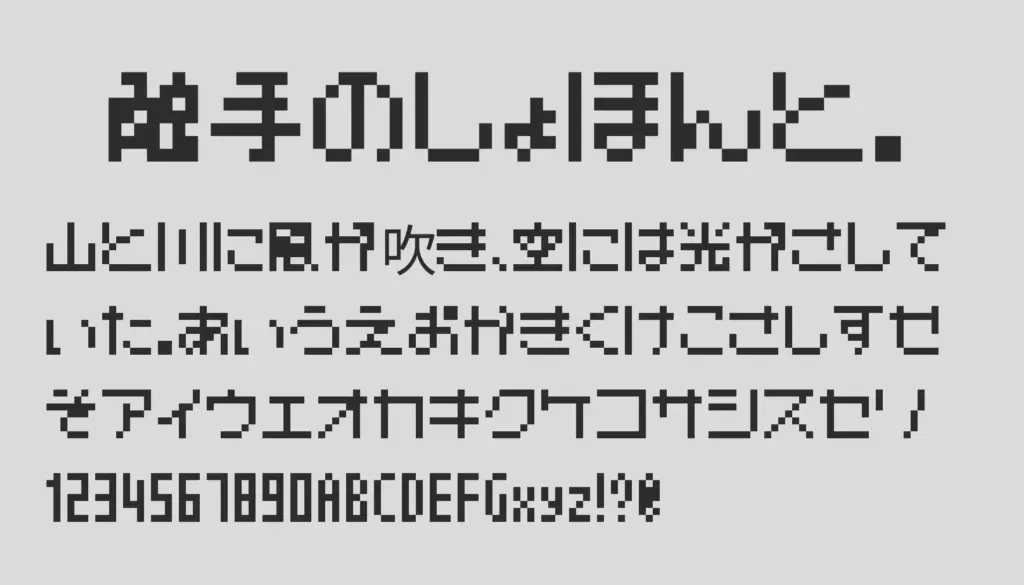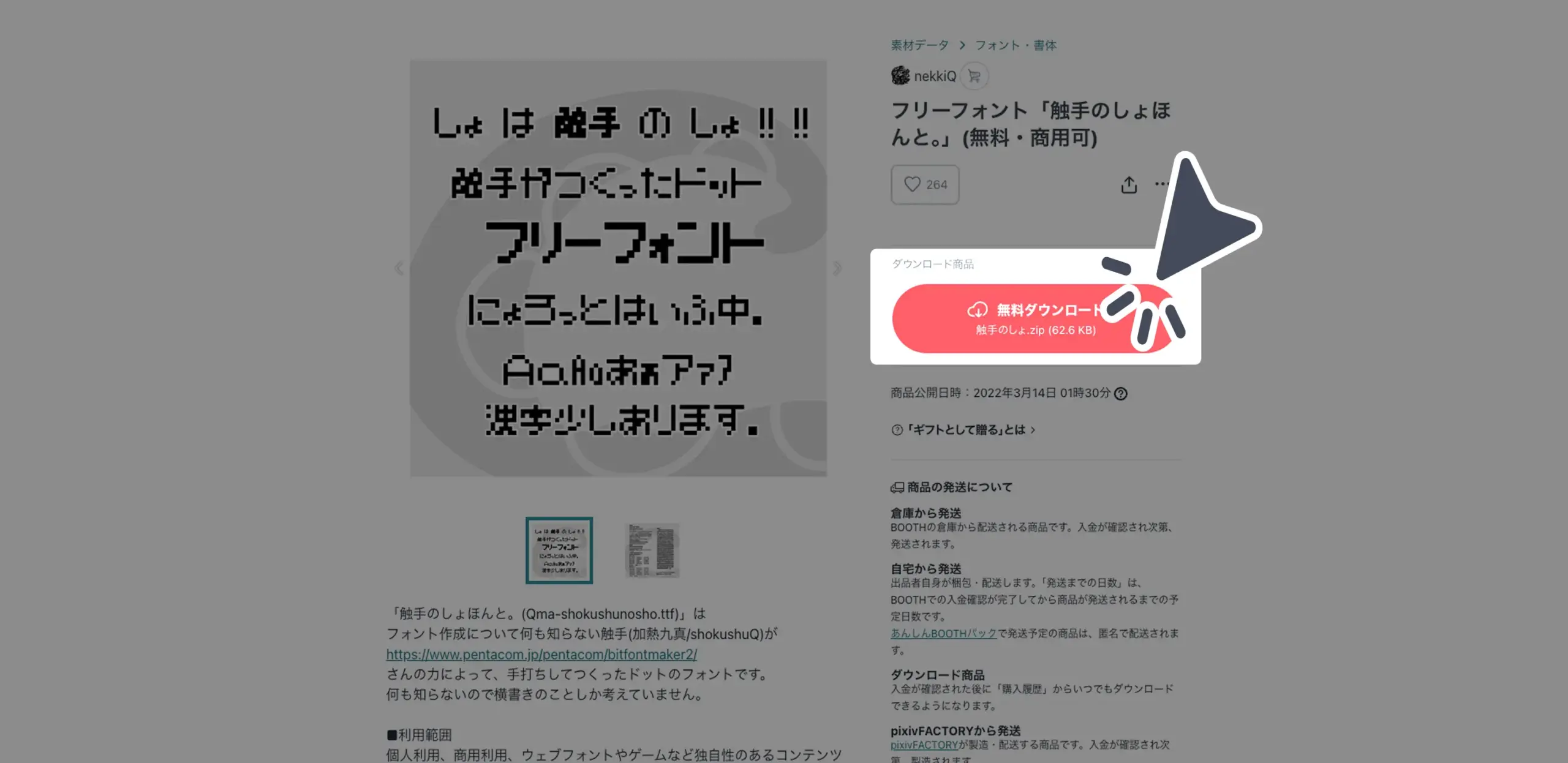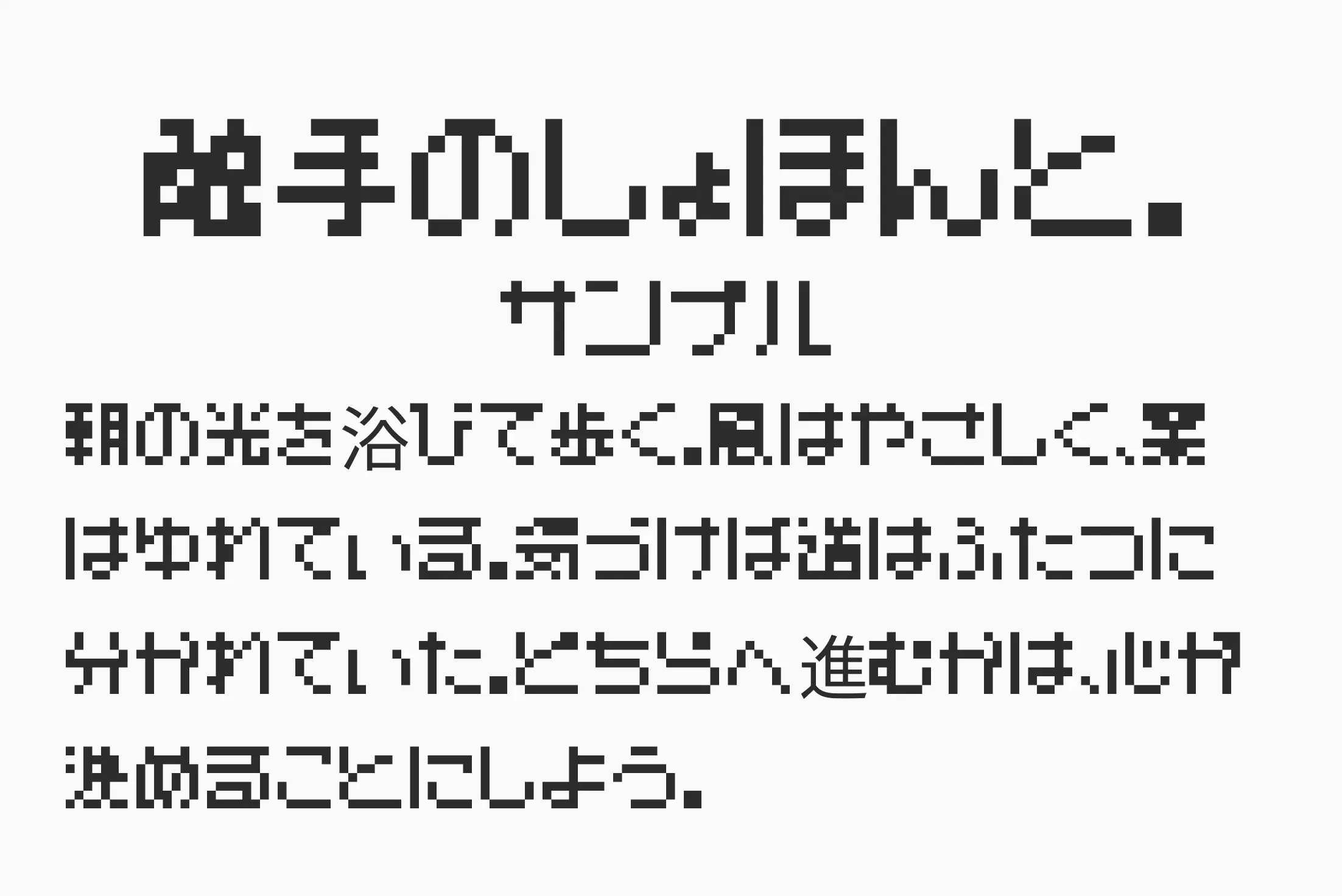
ドット感と触手感(!?)を融合させたユニークでサブカル系な角丸フォント。レトロゲームや実験的な世界観にぴったりの独自性があります。一見するとビットマップ風ながらも、読みやすさはしっかり担保。同人誌・ホラー・サイバーパンク・ネタ系ロゴなど、“クセ強め”な場面に映える存在感バツグンのフォントです。
触手のしょほんと。